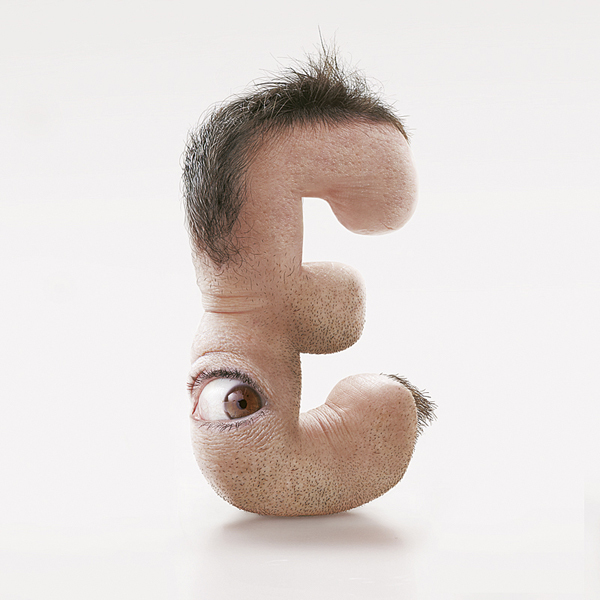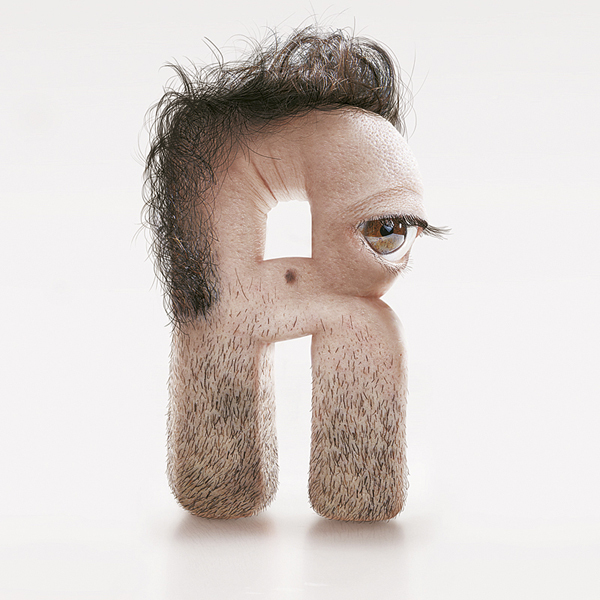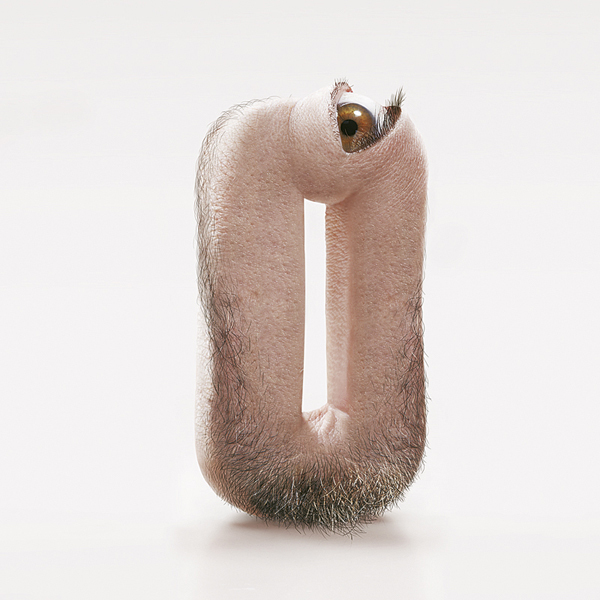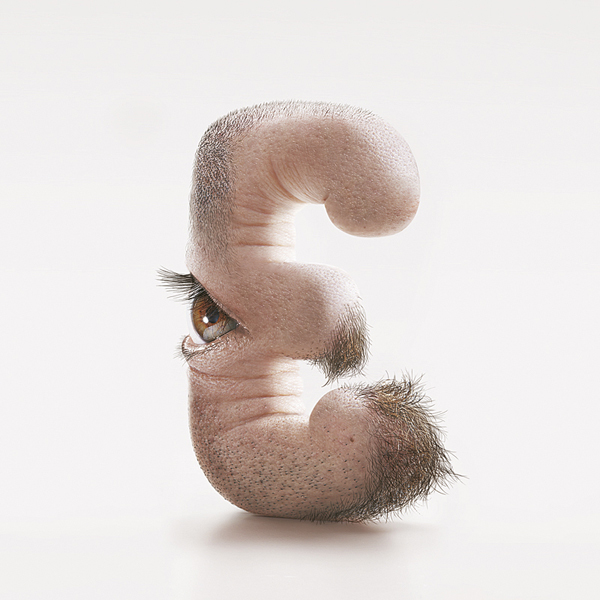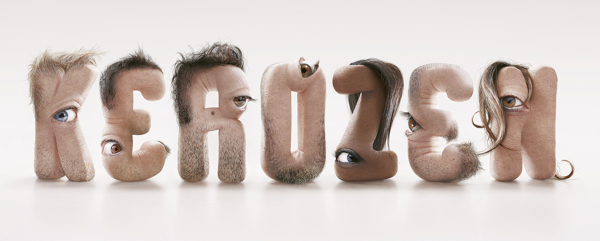
C’est une série de lettres humaines créée par Jean-Charles Debroize du studio de design Kerozen qui a pris le nom TypeFace au pied de la… lettre.
Des lettres à visages presque humain avec de la peau, des yeux, des poils et des cheveux.
Un peu tendance horrible.
Dans un style bien différent de l’alphabet 3D nostalgique de Ben Chelouche, voici les quelques lettre humaines (enfin…) qui forme le nom de l’agence KEROZEN: